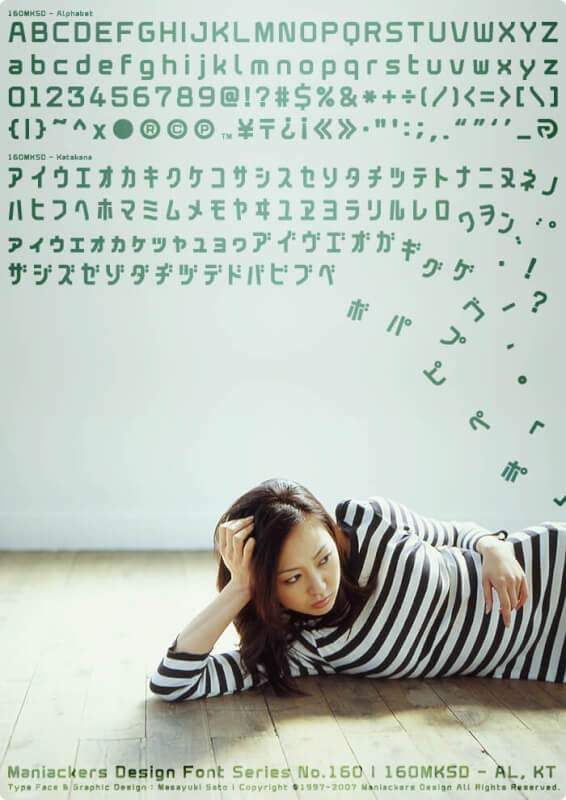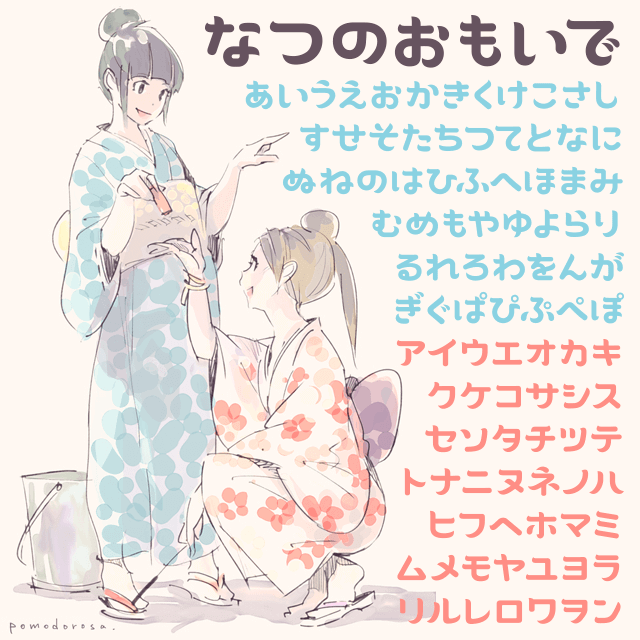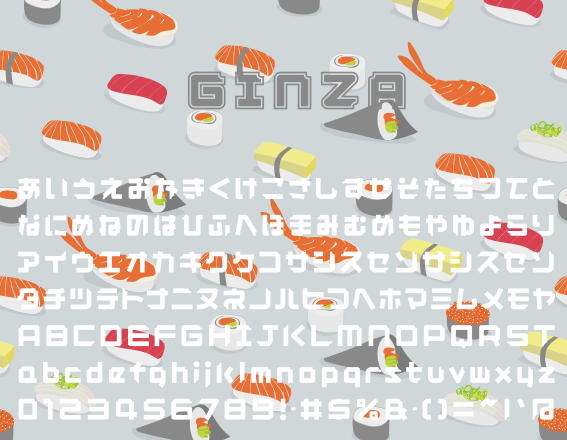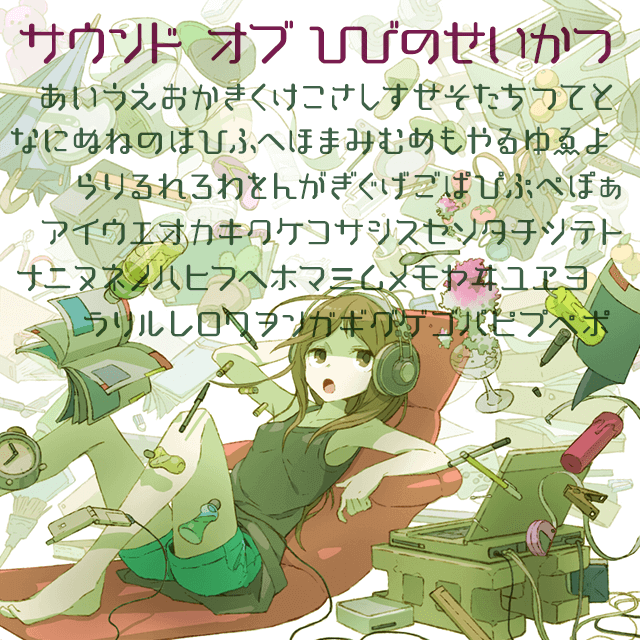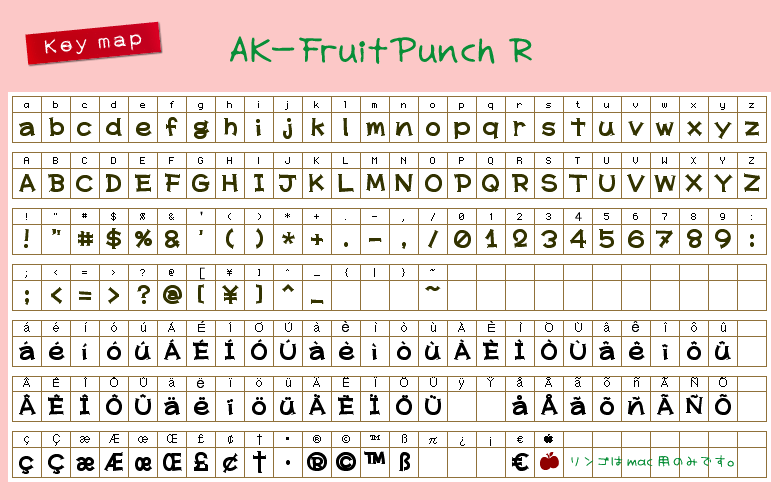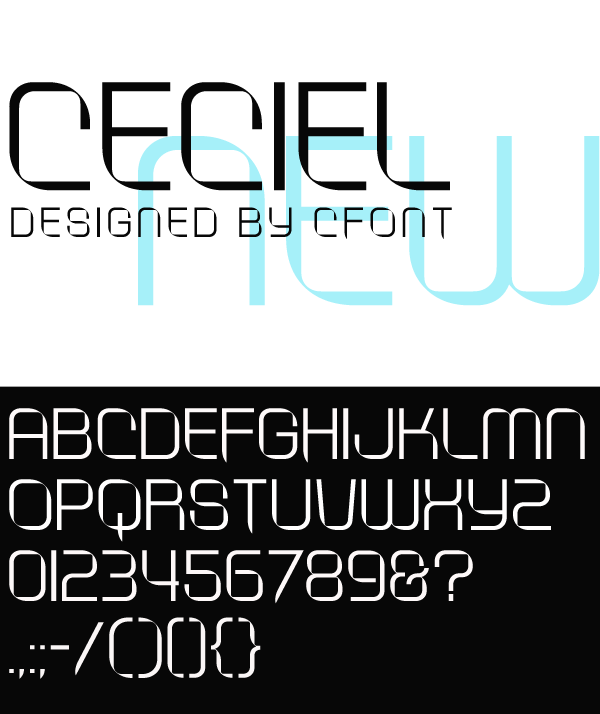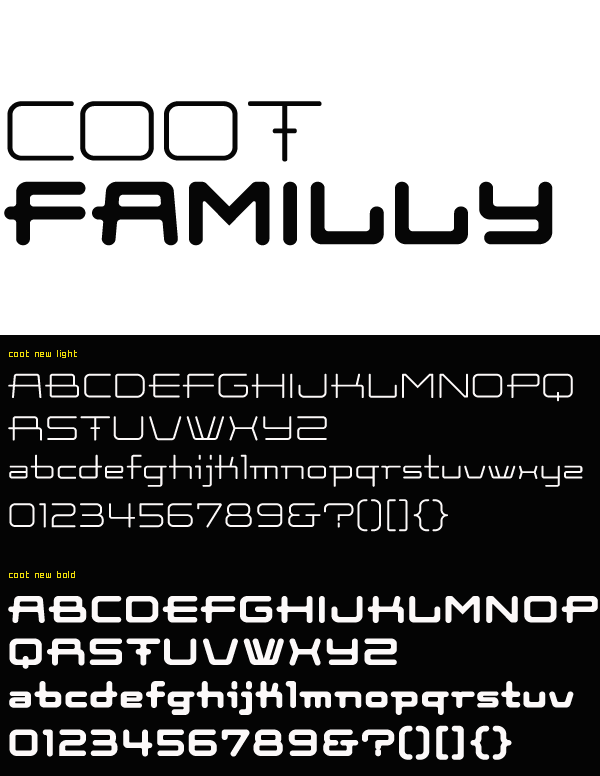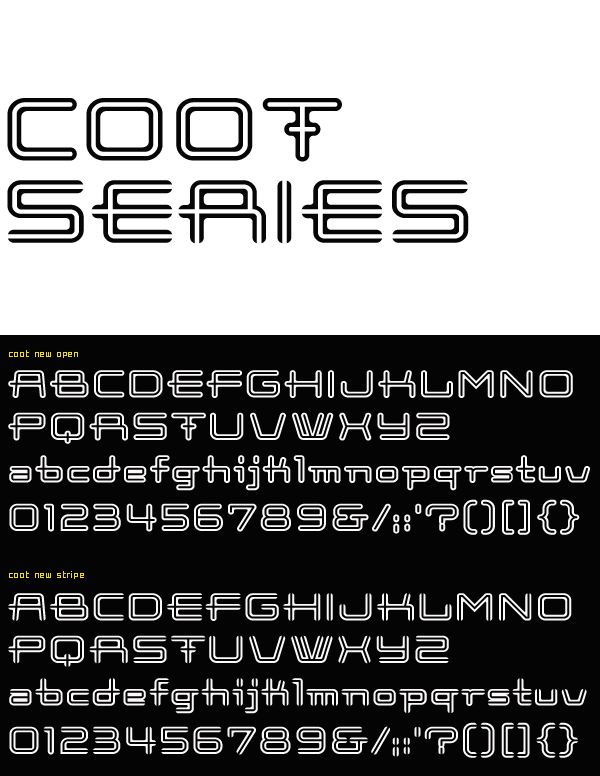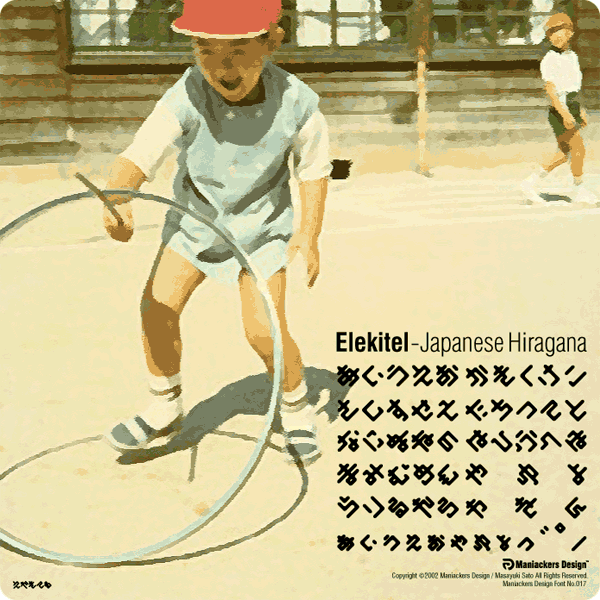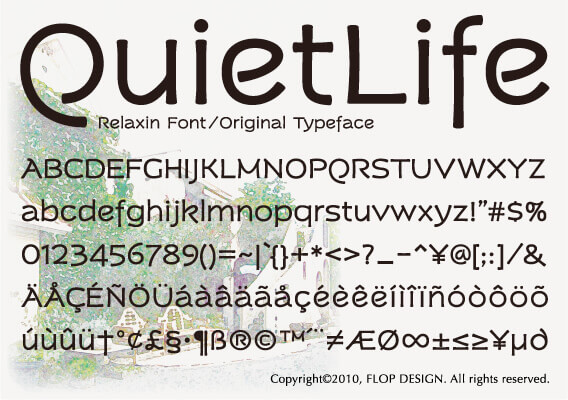
デザインされたオシャレな日本語・欧文フォント40選
入力するだけでオシャレなデザインにしてくれるフォントを40個ご紹介します。英語だけでなく漢字も使える日本語フォントもまとめています!お気に入りのお洒落フォントを見つけてモダンなデザインを作成する際にぜひ使ってみてください。
160MKSD-AL, KT
本文やロゴタイプデザインにも対応したオールマイティー、スタイリッシュな使いやすいフォント。
232MKSD Round – AL
全5ウエイトが収録されているフォント集。「Super Ultra Light」は、超極細ラインでデザインされているので、フォントサイズが45ポイント以上でないと、線幅が0.3pt以上の太さにならないので注意です。
243Ground-Alphabet
ラインの細い角丸でステンシルな欧文フォント。
Adorable Doll
ガリーな雰囲気があるデザインされたフォント。半角英数・一部記号を収録しています。
Adorable Lady
ガリーな雰囲気があるデザインされたフォント。半角英数・一部記号を収録しています。こちらは大文字の中にハートが入っていいます。
AK-FruitPunch H
ひらがな版フォント。1バイトなので、英数モードでキーボードのひらがなを見ながら入力可能です。
AK-FruitPunch R
アルファベット版フォント。アルファベットはなんと仏独に対応しています。
Ceciel
ラインとラインが重なる場所を細くしているおしゃれフォント。商用利用にはロイヤリティーフリーの「CFONT COLLECTION」を購入する必要があります。
Coot Family
lightとboldの2書体があり、boldは角丸の太めになっています。
Coot Open/Stripe
白抜きが特徴的な欧文フォント。ラインの最後が閉じている「open」と、開いている「stripe」の2種類があります。
Elekitel-HR
45度に傾けたアイディアが印象的なフォント。
FSB07 Astra-AL, KT, HR
英語とカナに対応したフォント。フォントファミリーも5つ収録されています。
Love Rocket
英語に対応しているフリーフォント。ロゴなどにオススメです。
Millkey Bold
文字のラインの一部に厚みをもたせているフォント。商用利用にはロイヤリティーフリーの「CFONT COLLECTION」を購入する必要があります。
Morphon
エレガントでキュートな丸みを強調したフォント。カフェなど飲食店のロゴやメニューに最適です。
Quietlife
ゆったりとした時間を感じさせつつも、今風の誌面にも合う「かわいさ」と「動き」のあるデザインされたフォント。
Root Normal
全体的に丸みをもたせた英語のフリーフォント。